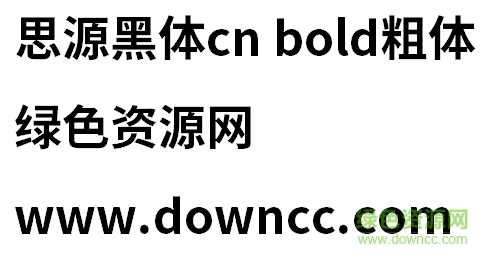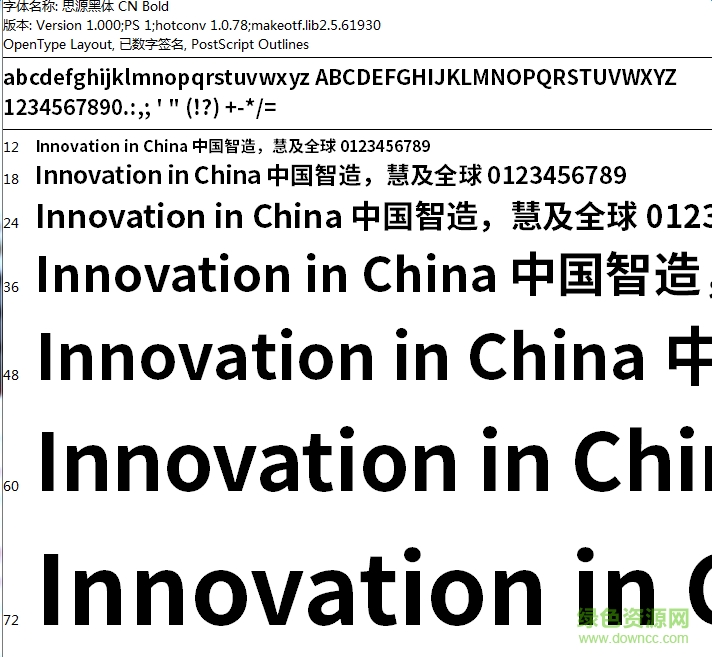
思源黑體cn bold粗體
思源黑體cn bold粗體是一款思源系列開源字體,作為思源黑體七大字體中的一款經(jīng)典字體,其優(yōu)美的筆畫深受廣大年輕人喜歡,更多好看的字體盡在綠色資源網(wǎng)!
思源黑體cn bold字體介紹
思源黑體是Adobe與Google歷時三年在2014年7月宣布推出的一款開源字體,這是一款新的供桌面使用的開源 Pan-CJK 字體家族, 有七種字體粗細(ExtraLight、Light、Normal、Regular、Medium、Bold 和 Heavy),完全支持繁體中文、簡體中文、日文和韓文,這些全部都包含在一種字體中,本次小編帶來的是思源黑體cn bold粗體!
思源黑體cn bold
很不錯的字體